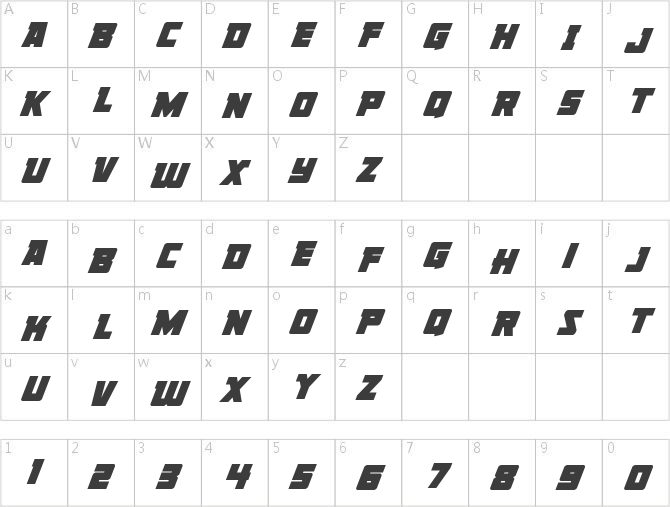
libertylegionsuperital 詳情頁
libertylegionsuperital字體字庫是一款讓人賞心悅目、百看不厭的英文字體,適合各類廣告和產(chǎn)品包裝設(shè)計(jì)應(yīng)用,字體大小0.03MB,格式為ttf字體,上傳用戶是Apple,作者/版權(quán)方為未知